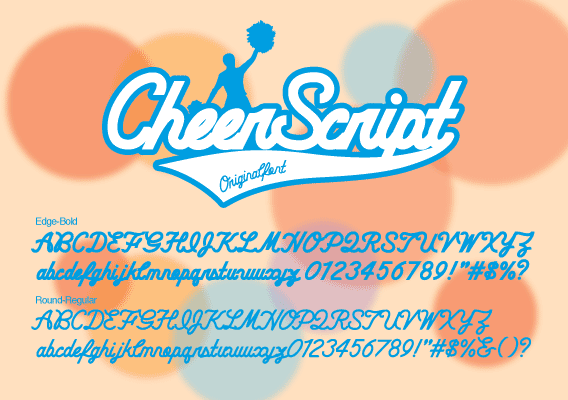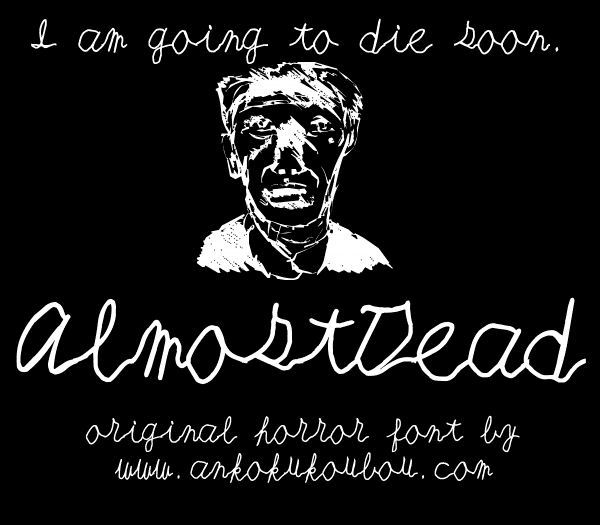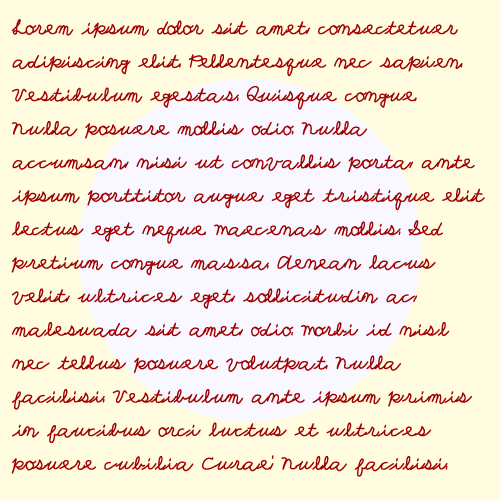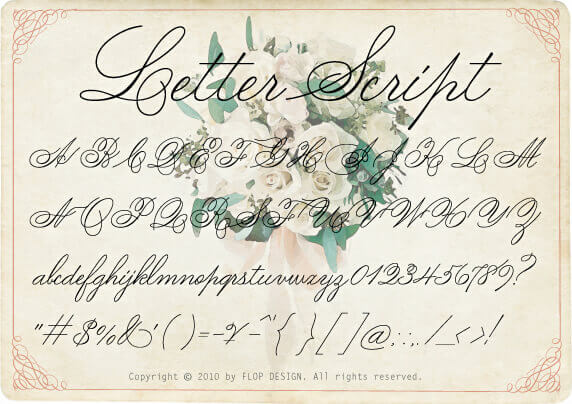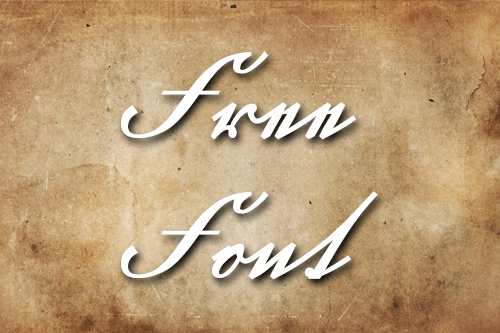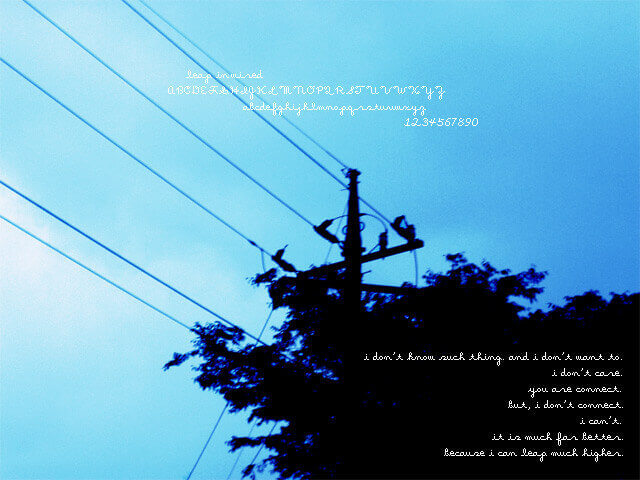
商用利用可能な人気の筆記体フォント一覧
多くのフォントの中でも人気の高い筆記体フォントをまとめてみました。ご紹介するフォントをインストールして文字を入力するだけでオシャレな雰囲気のデザインにすることができます。商用利用可能なフォントもありますのでご参考にください。
AK-My Prince
つながる筆記体をイメージしたフォント。大文字と数字はクルッとしています。
AlmostDead
死にかけ筆記体英字フォント。ダイイングメッセージなどの死にそうな人間が書いた文字をイメージしたデザインになっています。
AlmostDeadBloody font
死にかけ血滴る筆記体英字フォント。ダイイングメッセージなどの死にそうな人間が書いた文字をイメージしたデザインになっています。
GL-Suetterlin
ジュッターリン体。ドイツ文字(亀の甲文字)の筆記体フォント
leap in wired
筆記体ビットマップフォント。
Little Spirit
カッパープレート体のビットマップフォント。
Monolin
子供が書いたようなあたたかみのある筆記体フォント。
Spirit
カッパープレート体のビットマップフォント。
チアスクリプト
流れるような斜体が特徴的なフォント。
レタースクリプト
古い古い手書きの筆記体からデザインしたフォント。結婚式やプレゼントカードなどに使うとよいでしょう。